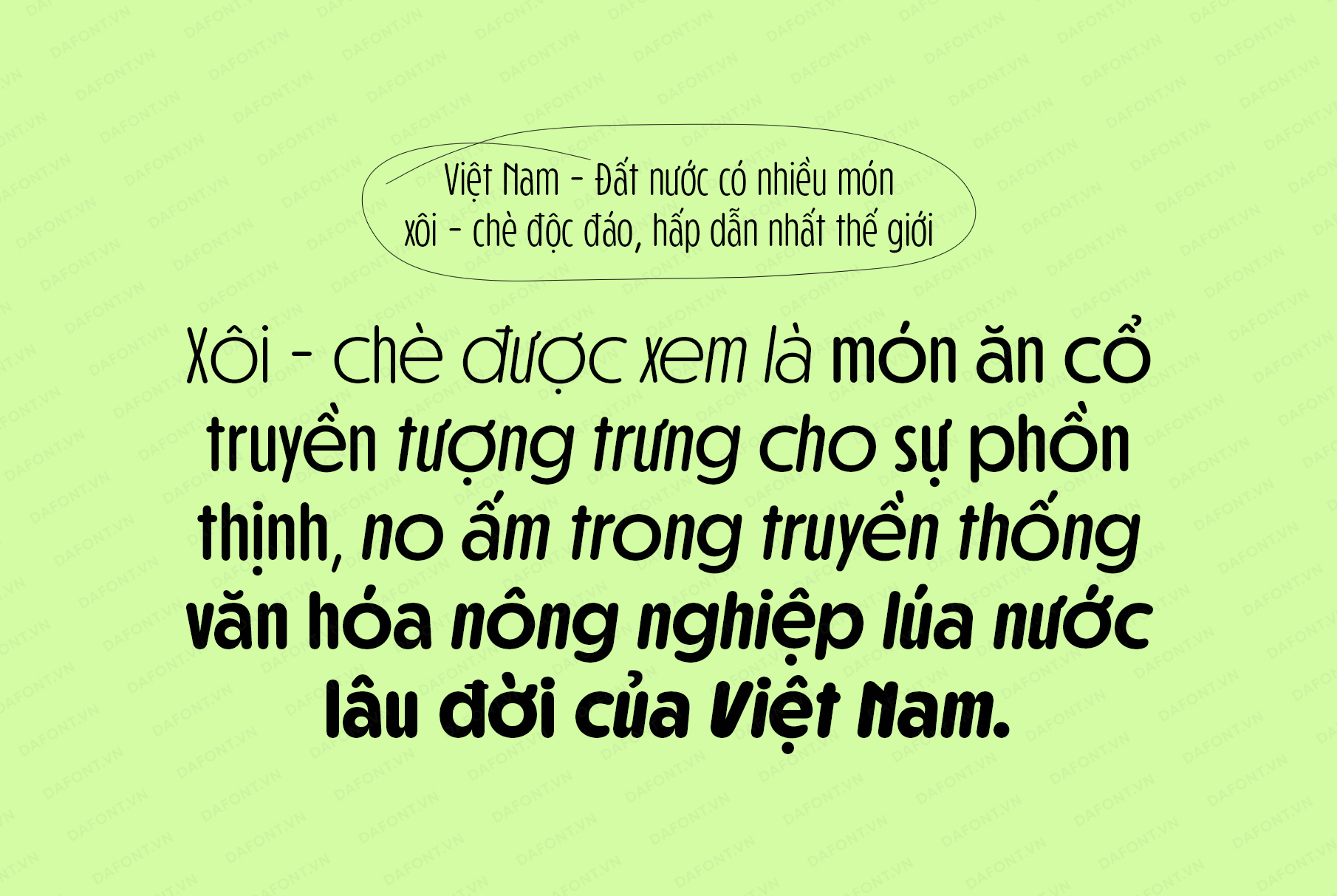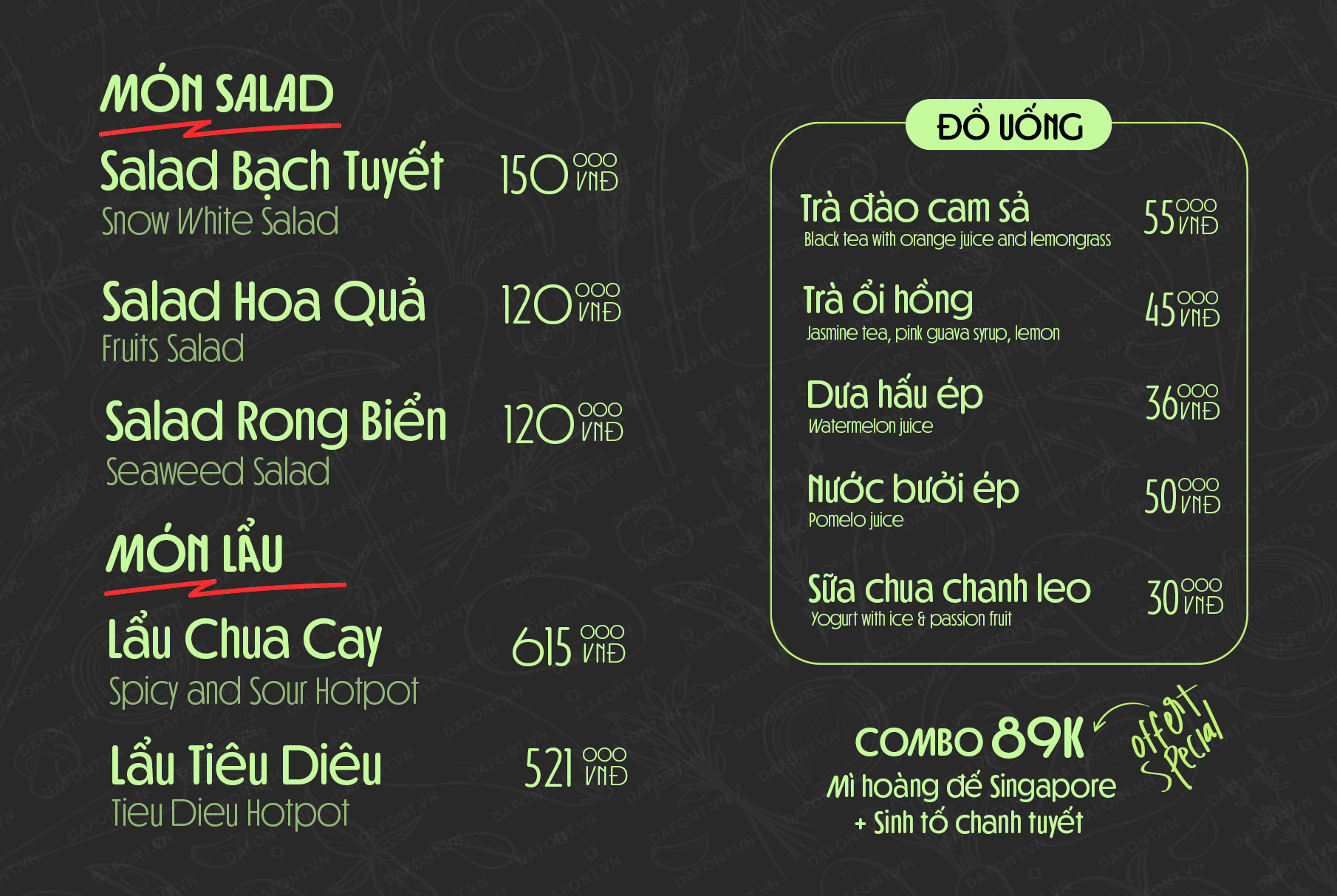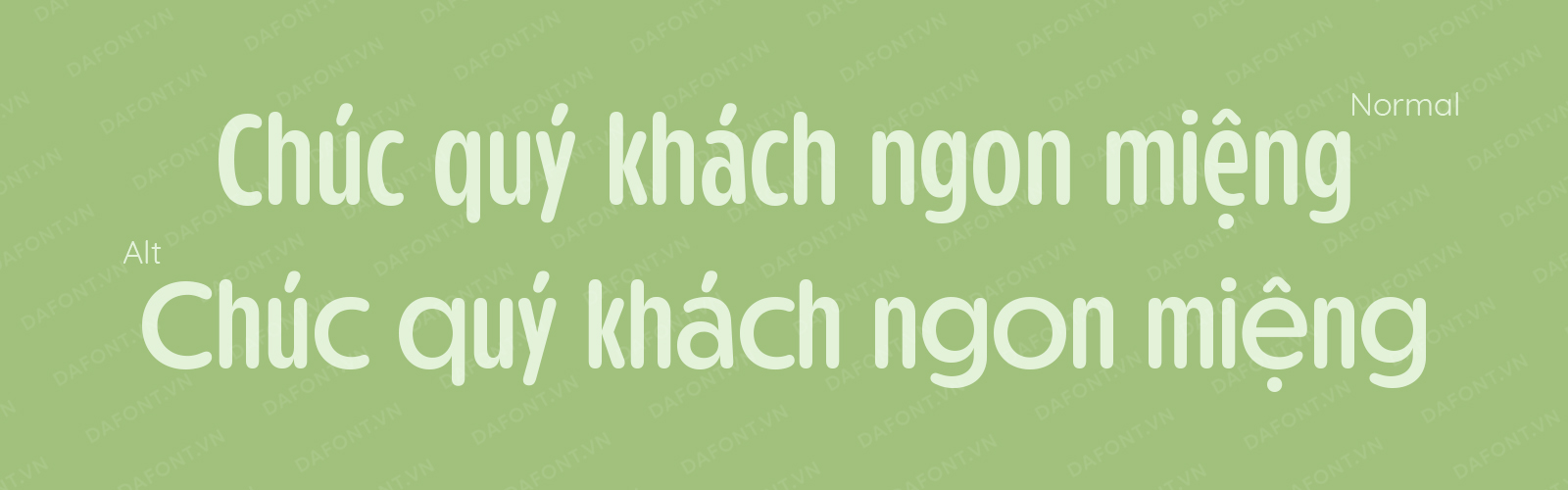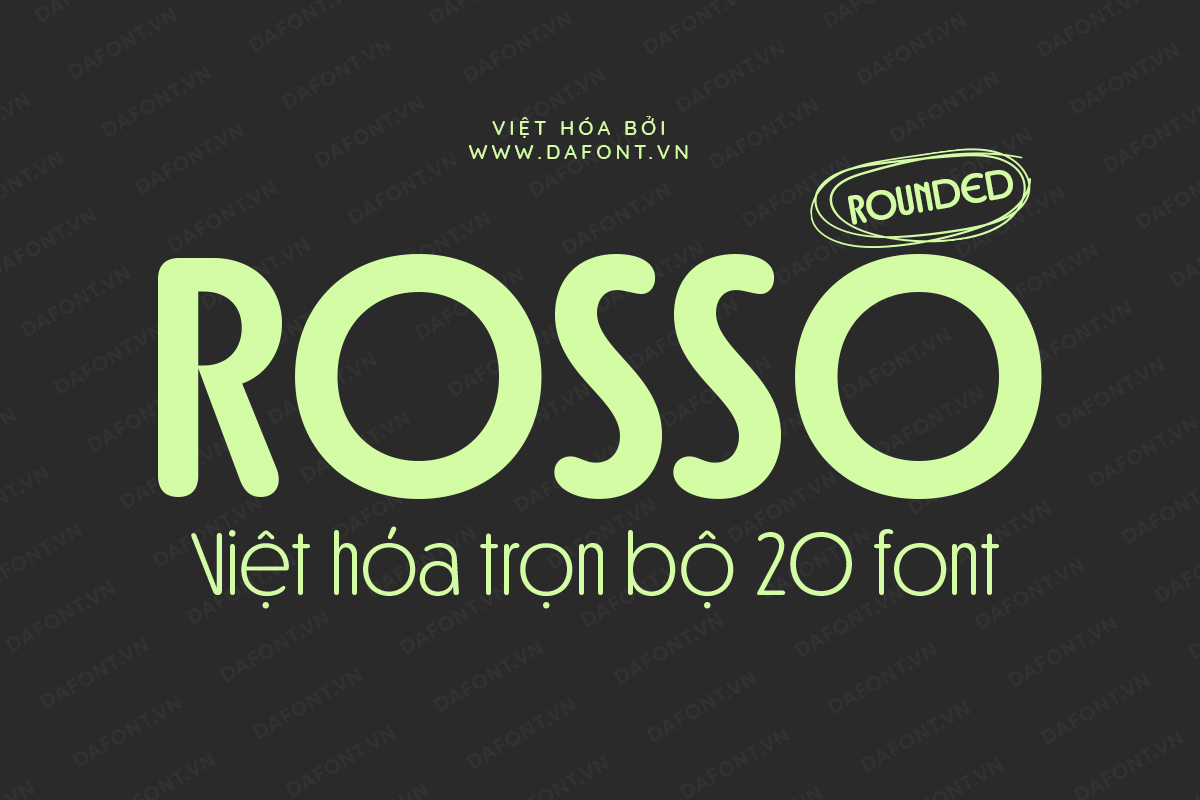
DFVN Rosso Rounded là phiên bản với các ký tự được bo tròn của kiểu chữ Rosso gốc. Bộ font này nổi bật với các đường nét tròn trịa và mềm mại, tạo cảm giác thân thiện và dễ tiếp cận.
Giống như phiên bản tiền nhiệm của nó, Rosso Rounded được thiết kế với cấu trúc hình học (geometric) và cô đọng (condensed structure). Với sự cân bằng tốt giữa chiều rộng và chiều cao của các ký tự, đảm bảo rằng chúng dễ đọc ngay cả ở kích thước nhỏ.
Rosso Rounded có 10 biến thể khác nhau từ Ultra Light đến Black với chữ nghiêng tương ứng. Ngoài ra, nó được chia thành hai phân nhóm là Normal và Alt.
Phiên bản Normal với các ký tự hẹp, phiên bản Alt các ký tự rộng hơn. Với hình dạng tròn của nó tạo ra sự tương phản trực quan mang lại cho nó một nét tươi mới vì vậy DFVN Rosso Rounded không chỉ đáp ứng nhu cầu sử dụng mà còn mang lại giá trị thẩm mỹ cao.
DFVN Rosso Rounded lý tưởng cho nhiều dự án thiết kế khác nhau như xây dựng thương hiệu, logo, áp phích, quảng cáo, menu nhà hàng, bao bì sản phẩm…. Nhìn chung, đây là một bộ font chữ có cá tính riêng, hoàn hảo để thêm nét hiện đại và thân thiện cho bất kỳ tác phẩm đồ họa nào.
Bộ font DFVN Rosso Rounded được việt hóa rất kỹ, từng dấu được tối ưu hóa lại để hiển thị tốt khi sử dụng ở kích thước lớn và văn bản nhỏ. Ngoài ra, bộ font được kering đầy đủ, dễ dàng sử dụng tính năng Opentype. Bộ font cũng được tối ưu hóa để bạn có thể dễ dàng sử dụng nó trong bất kỳ phần mềm thiết kế nào.